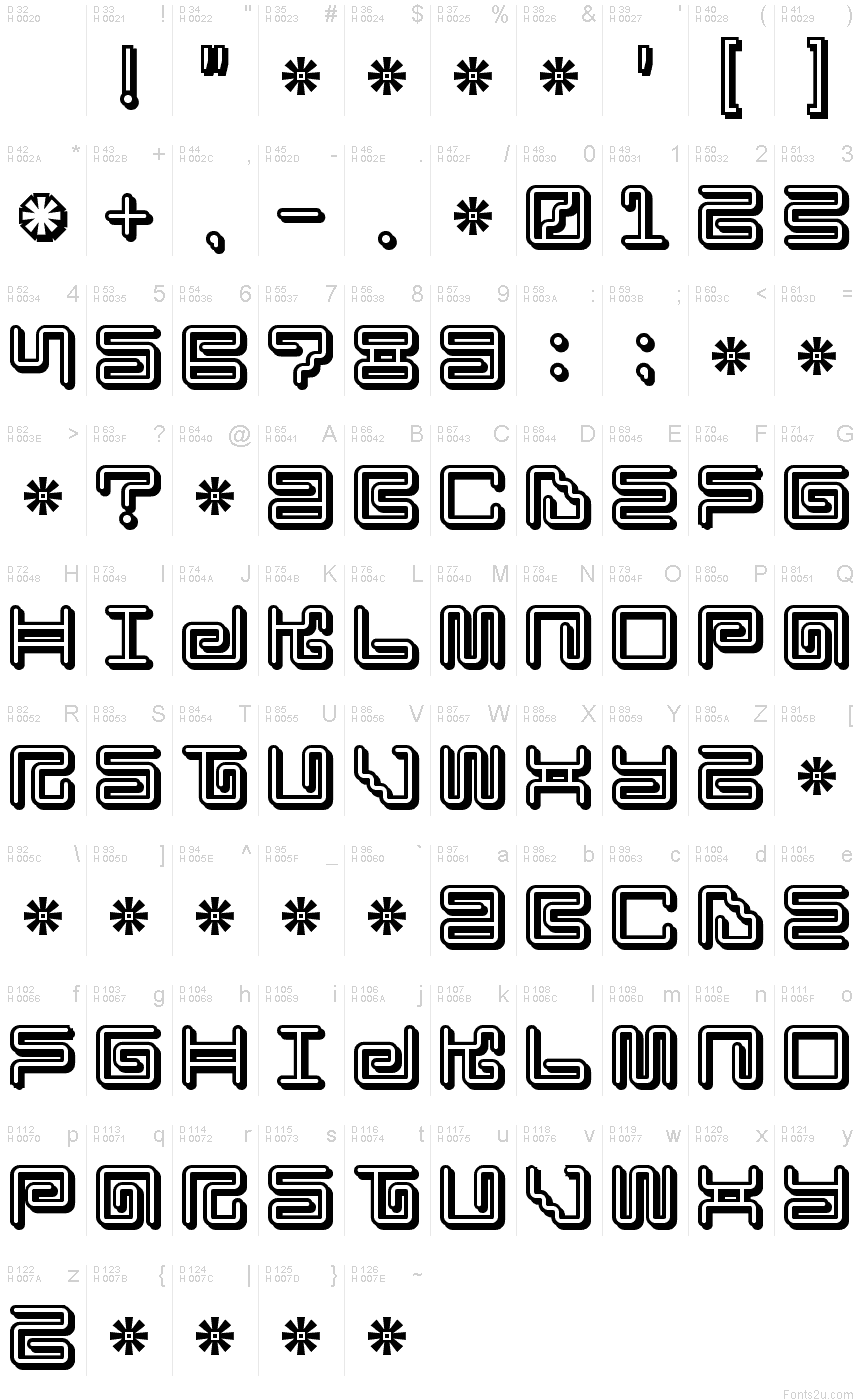
Iron Lounge Smart
Iron Lounge Smart di Jakob Fischer è un carattere display in stile groovy con una costruzione audace, simile a un tubo, che trasmette un’atmosfera al contempo retrò e futuristica. Ogni lettera si attorciglia come un neon in un labirinto, con spessi contorni neri che racchiudono interni luminosi e aperti, conferendo ai glifi un aspetto massiccio, quasi gommoso. Sembra disegnato con un unico tratto continuo, permettendo alle parole di unirsi in un ritmo fluido che balza fuori dallo schermo o dalla pagina.
Con Iron Lounge Smart, i tuoi titoli acquisiranno immediatamente quell'energia lounge-club e synthwave: è perfetta per poster, volantini per eventi, copertine di album o mixtape, titoli di videogame, merchandising e accattivanti banner per i social media. Questo font gratuito dà il meglio di sé nei grandi formati, dove le sue curve intricate e le forme delineate possono respirare; per i testi più piccoli, abbinalo a un carattere sans serif pulito e geometrico per mantenere la leggibilità, lasciando che il lettering principale diventi il protagonista assoluto.